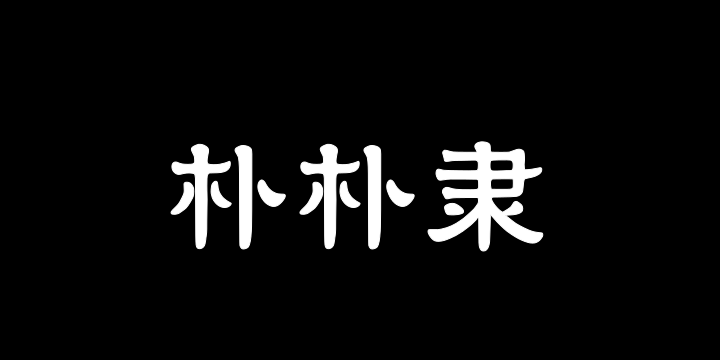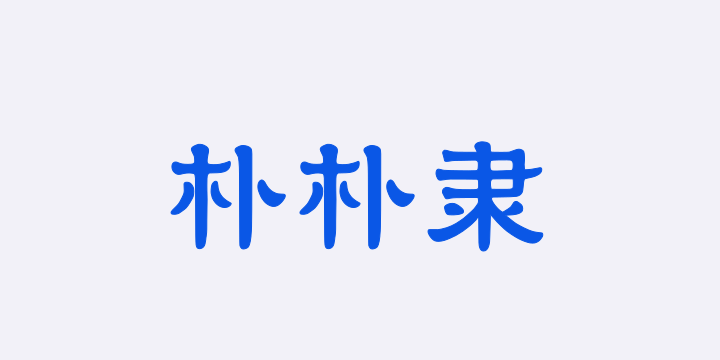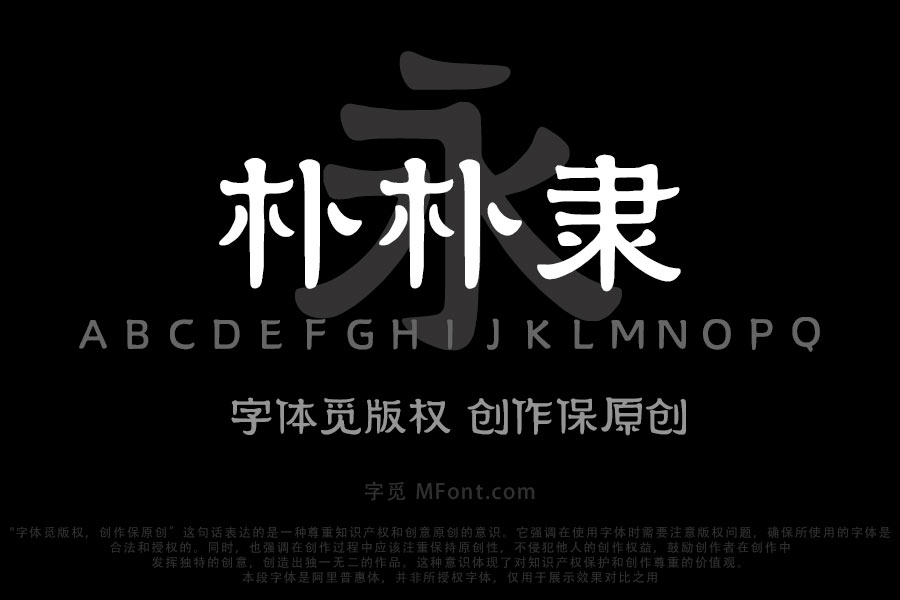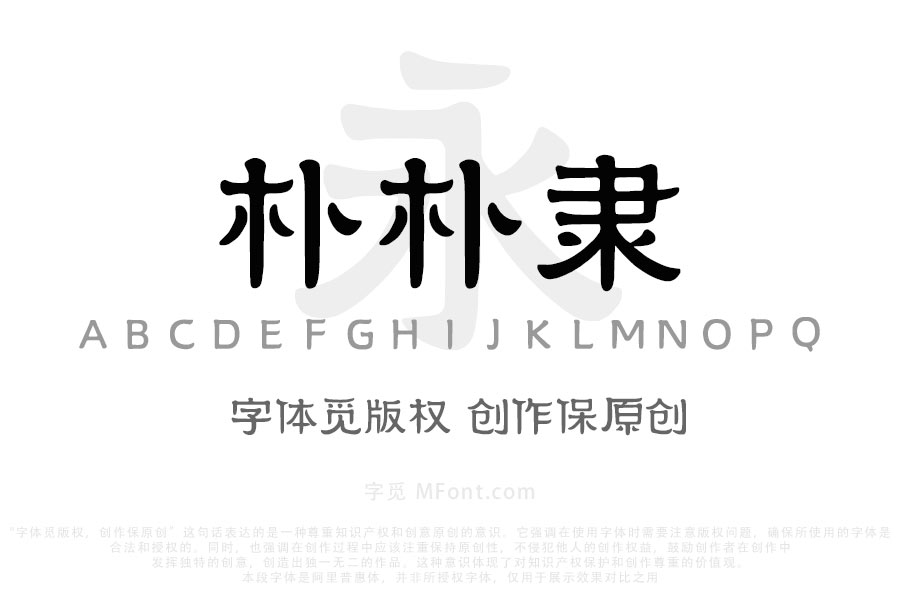
字潮朴朴隶
字潮字库
关于字潮朴朴隶字体字库信息
字体全名: 字潮朴朴隶
铸字厂: 字潮字库
设计师: 丁道华
字体简介: 字潮朴朴隶将传统毛笔书法的神韵与现代字库的规整性完美融合。字体重心平稳,结构严谨,确保了在大量文本应用或标题展示时,既能传递出东方古典文化的深厚底蕴,又不失清晰易读的实用性。
所属分类: 隶书手写体